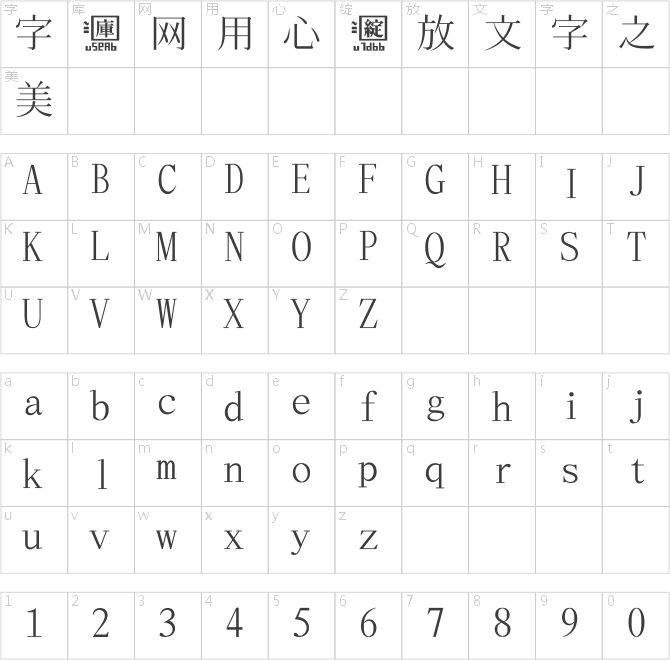
字體名稱: 香港民間字集
作者版權: Henry C
香港民間字集字體下載HKCS Traditional Orthography
香港民間字集(HKCS)是一項在明代字體中創建現代和歷史漢字字體目錄的項目。這是一種支持傳統正字法的襯線字體,它是由@SyaoanHinata所勾畫的。傳統的正字法是比較適合現代甲骨文、青銅銘文和小印章詞源研究的。此版本的字體包括Uro/Uro+中的所有字符,并從分機A/B中選擇字符,以便在香港支持粵語。